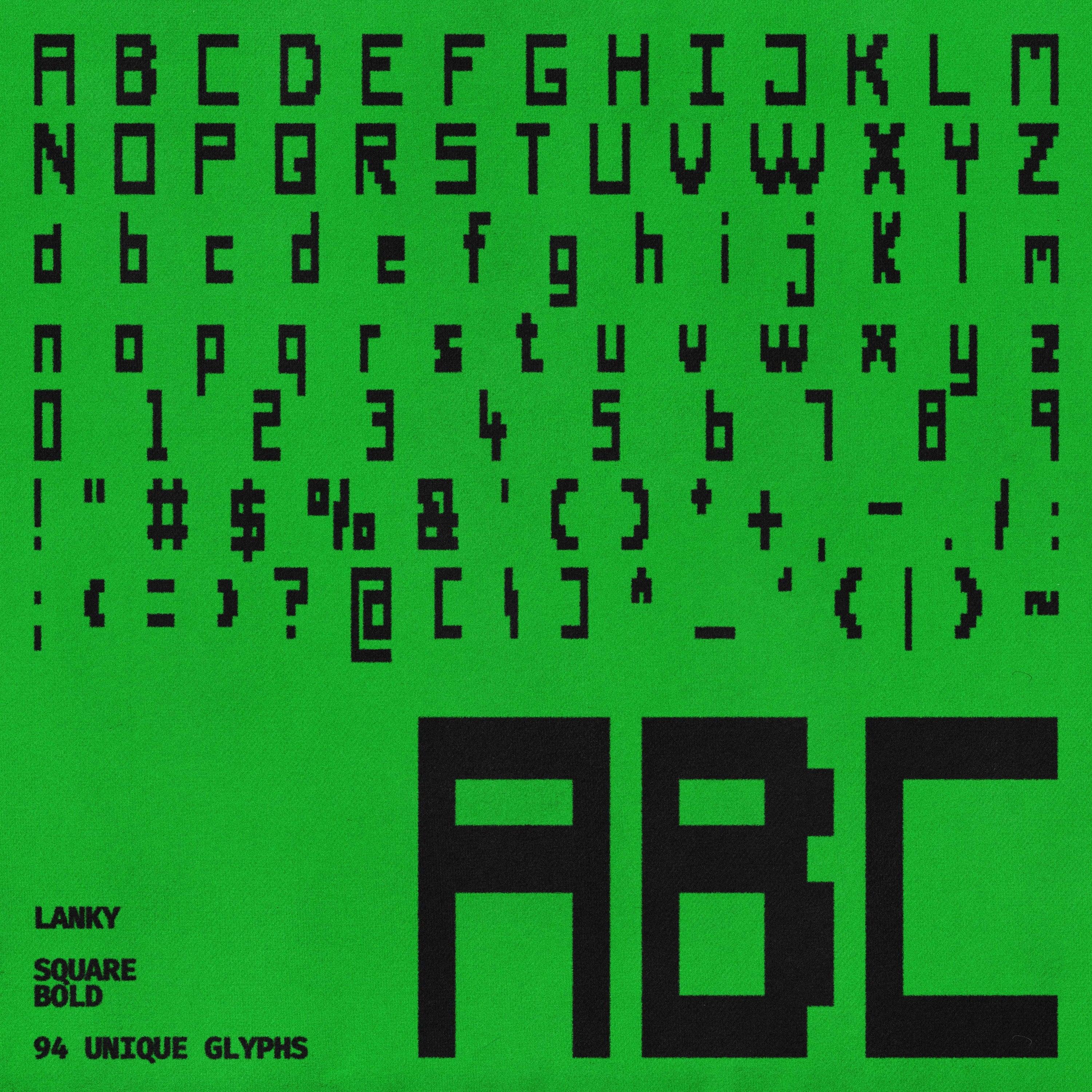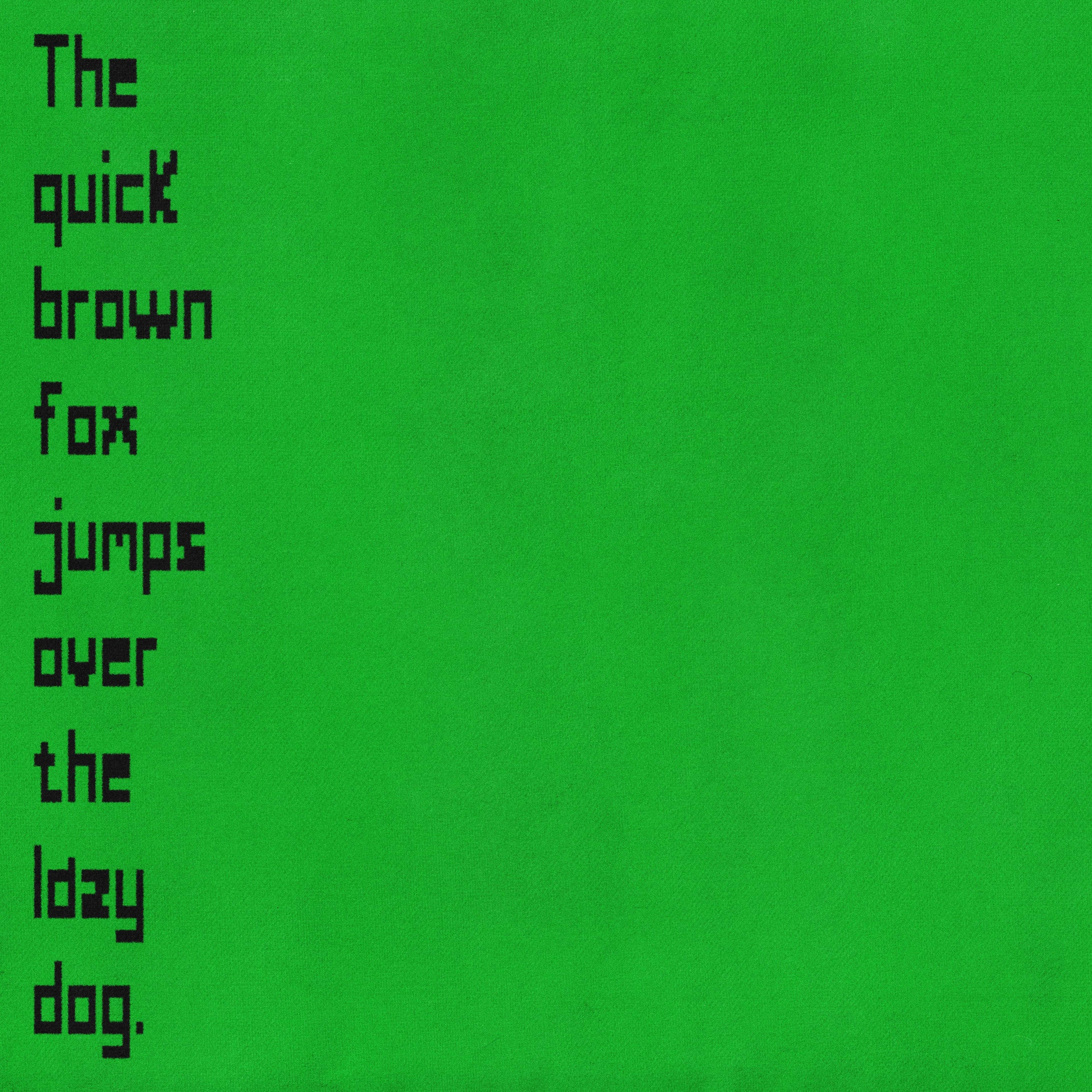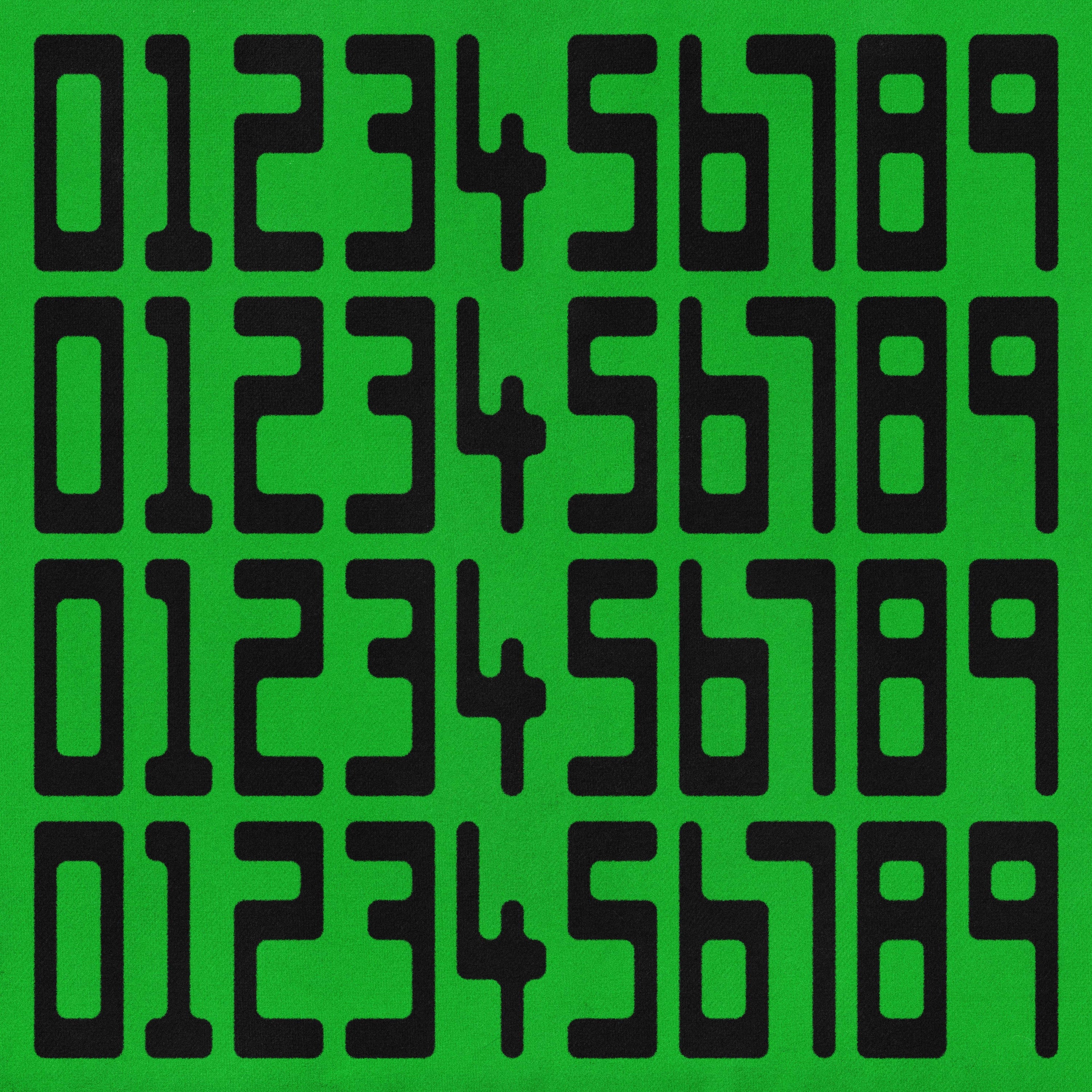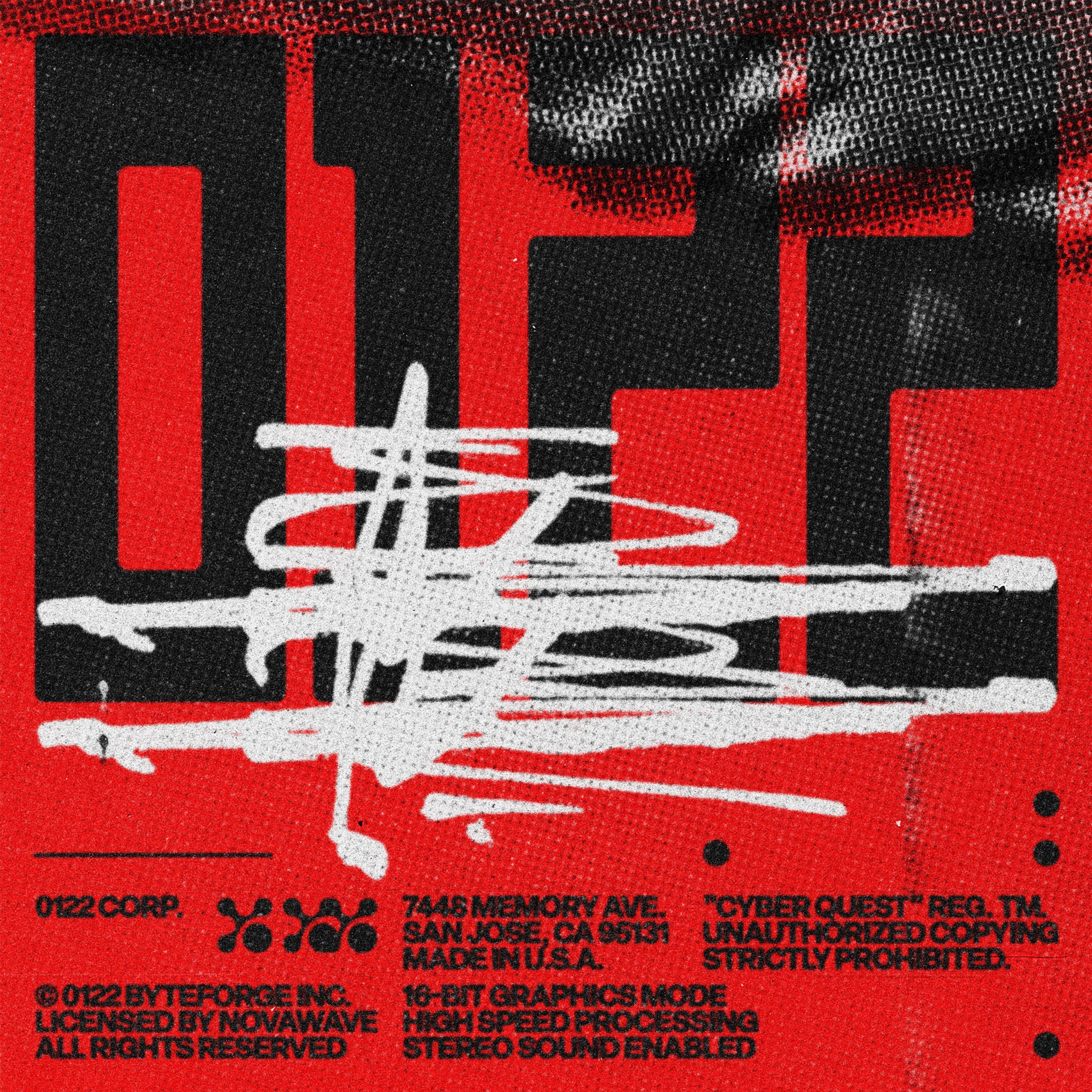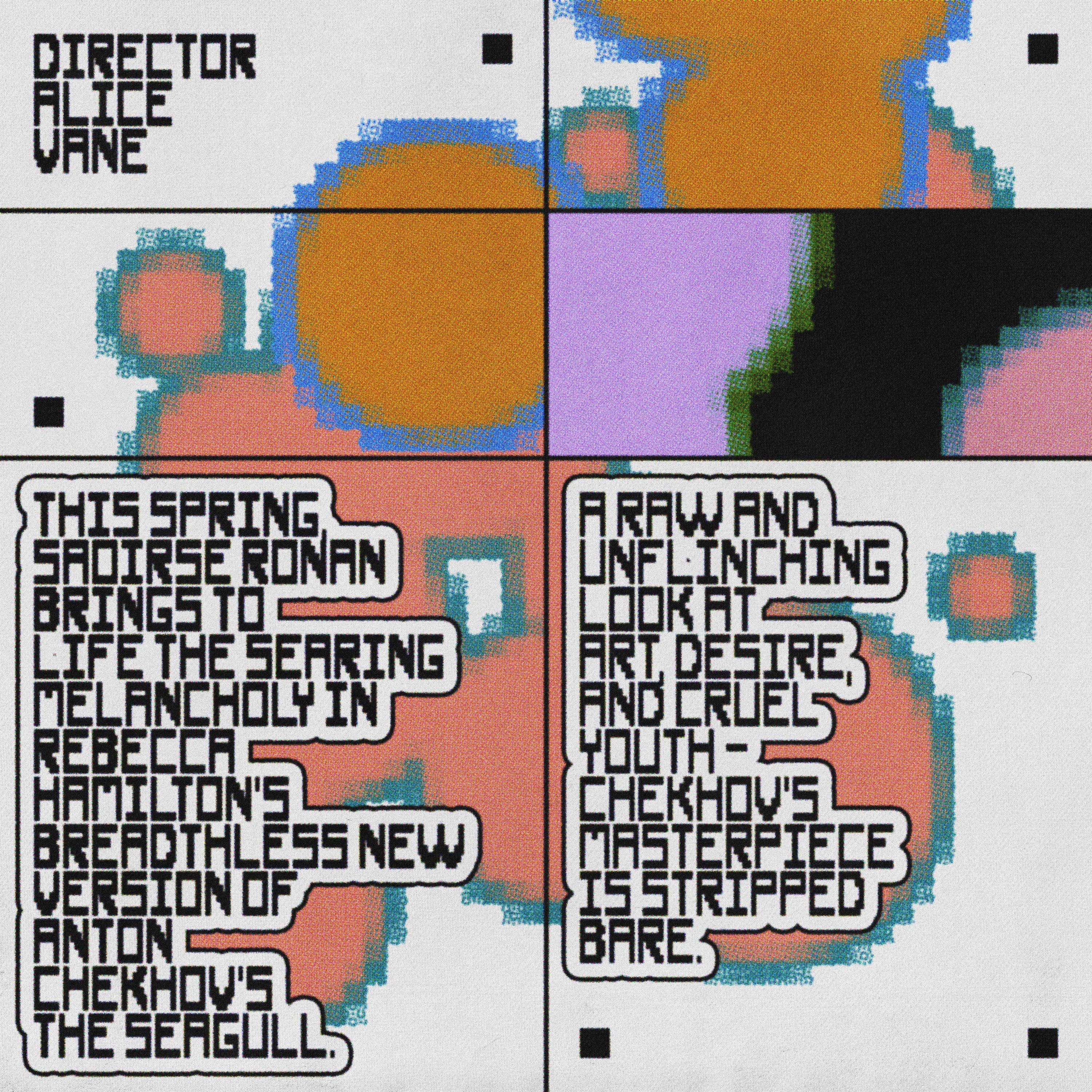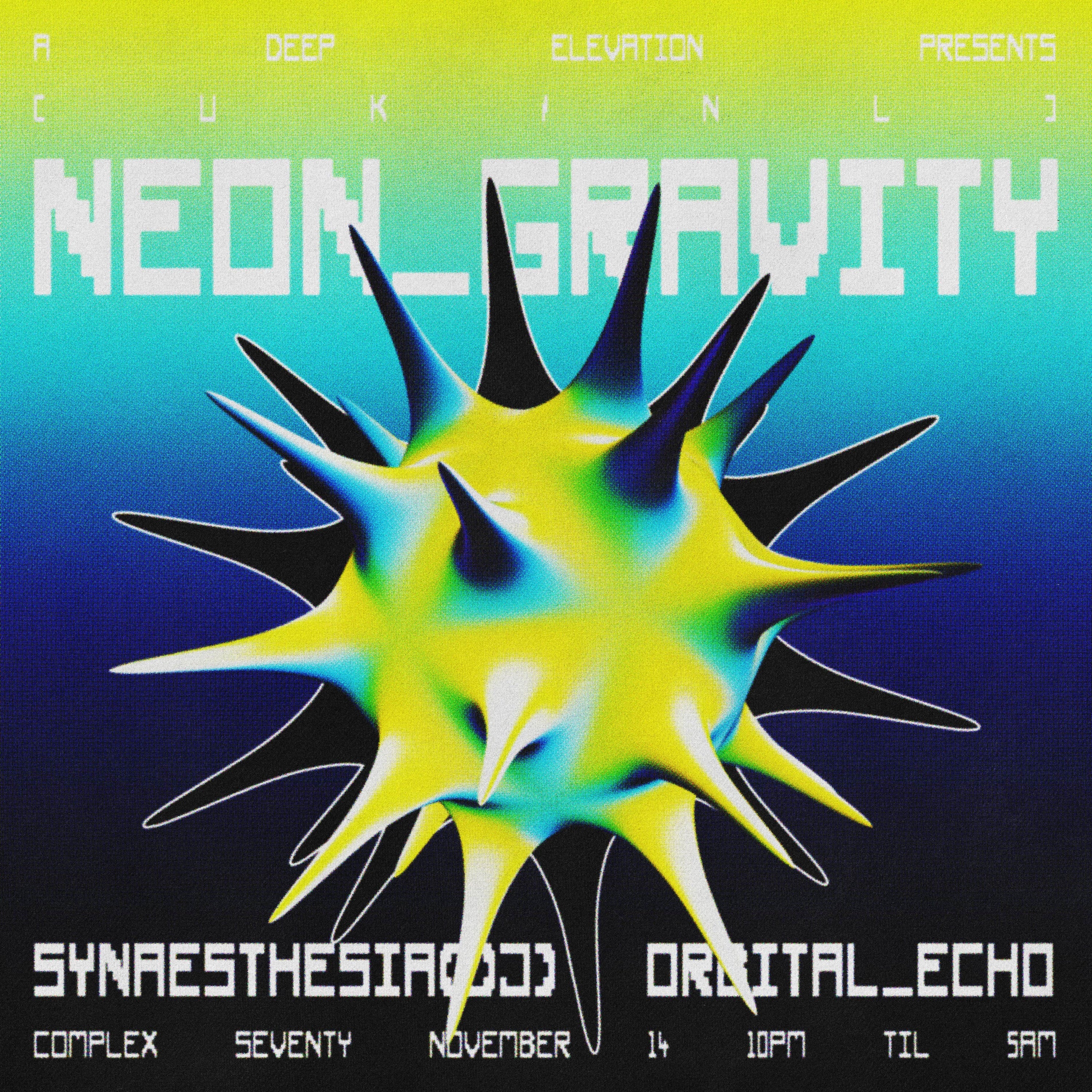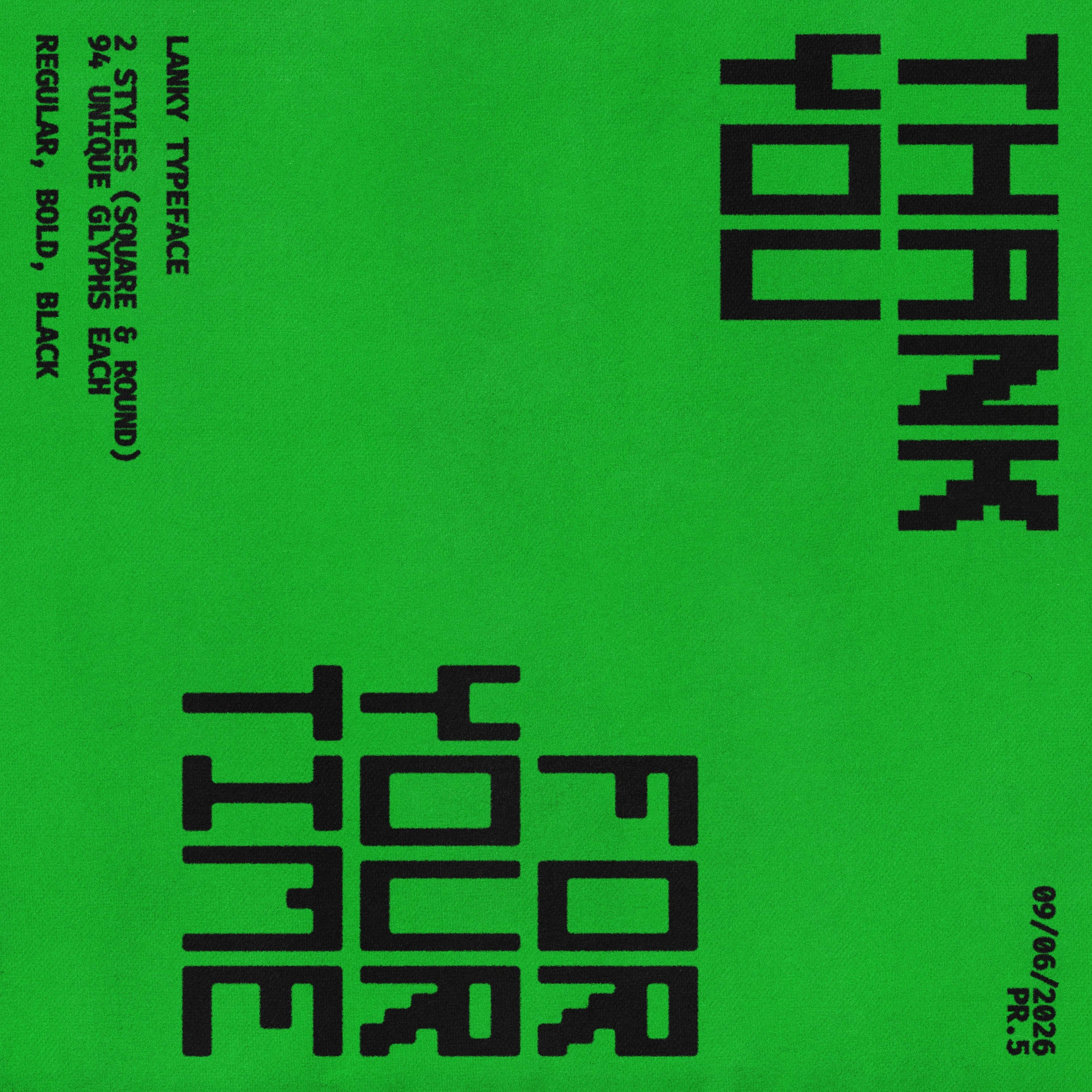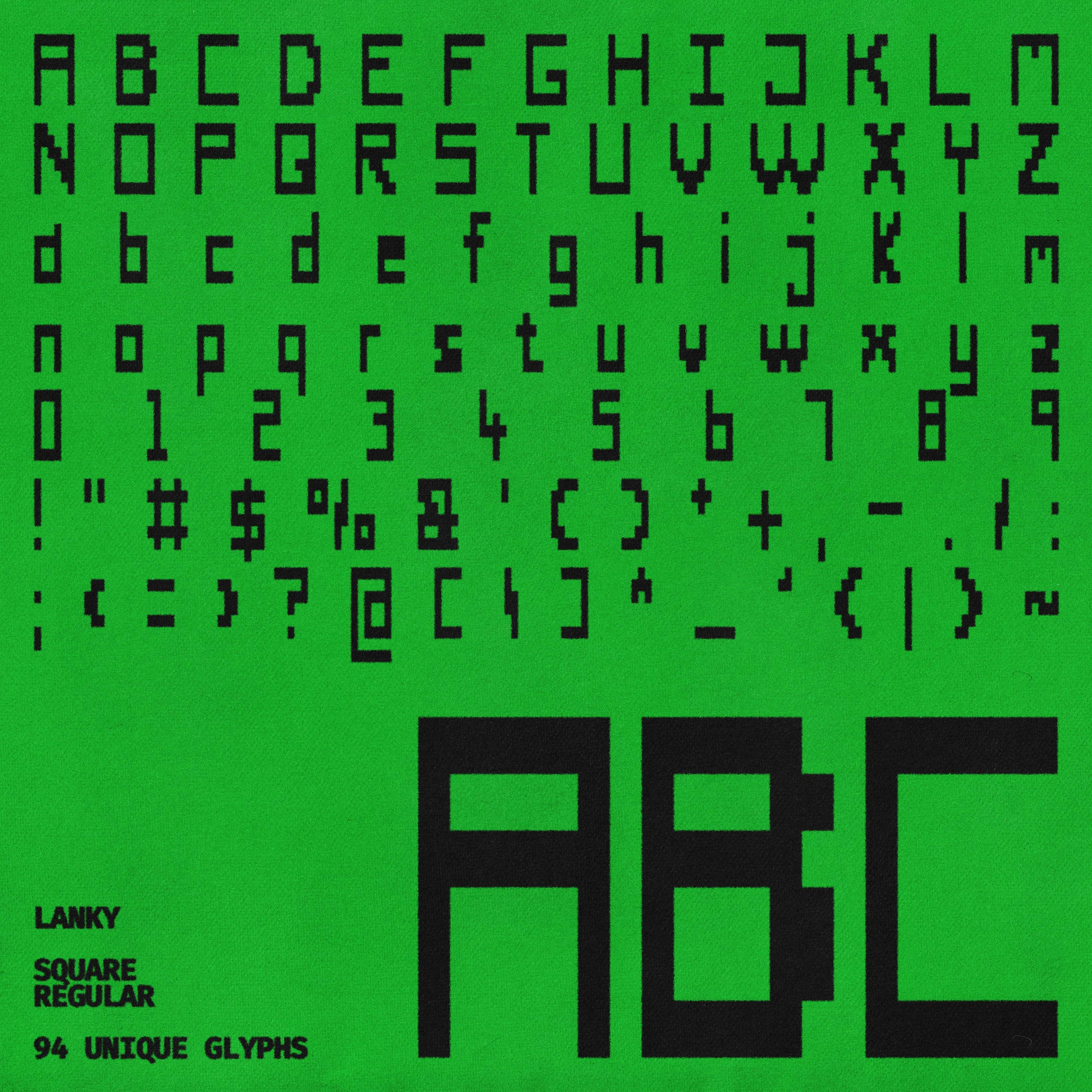
Lanky Typeface
Lanky é uma tipografia display ultralta, criada para causar forte impacto visual por meio de proporções extremas e estrutura arquitetônica. Suas formas estreitas e alongadas criam um ritmo distinto que chama a atenção instantaneamente.
Disponível em dois estilos — Square e Round —, Lanky equilibra uma construção geométrica rígida com detalhes curvos mais suaves, oferecendo versatilidade para diferentes direções criativas. Sua presença marcante a torna ideal para tipografia em grande escala, na qual impacto e reconhecimento são importantes.
Perfeita para branding moderno, layouts arquitetônicos, pôsteres, peças gráficas de moda, títulos editoriais, embalagens e sistemas de identidade contemporâneos.
Características
• 94 glifos
• 6 estilos (Square Regular, Square Bold, Square Black, Round Regular, Round Bold, Round Black)
• Minúsculas
• Maiúsculas
• Números
• Pontuação
• Símbolos
• Matemática